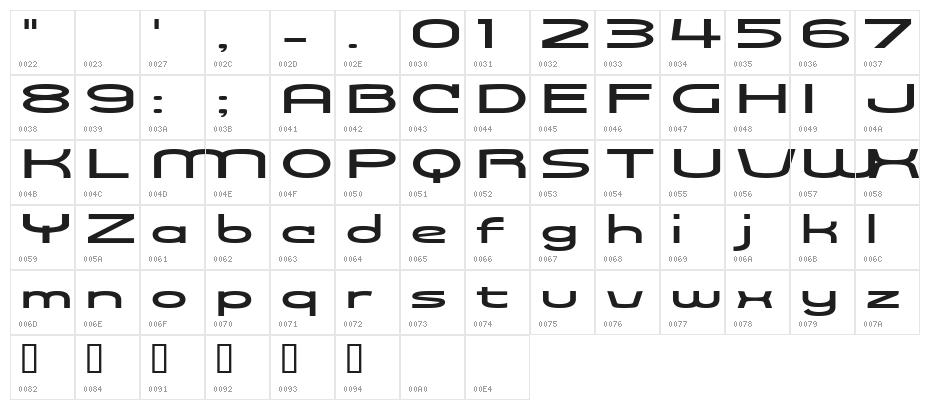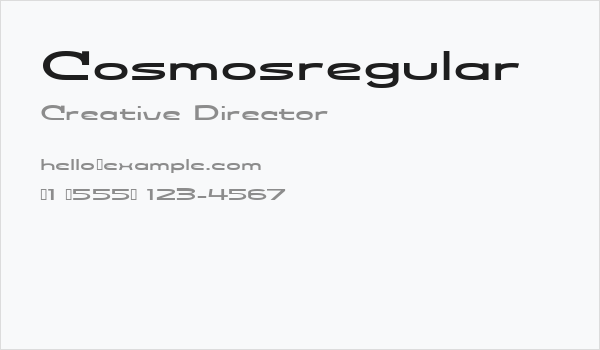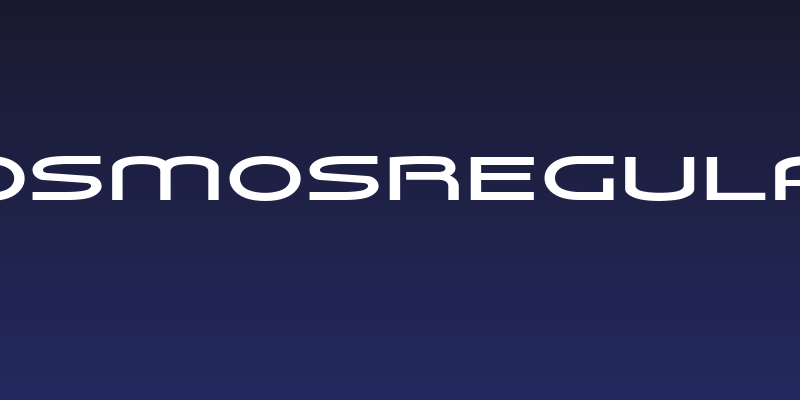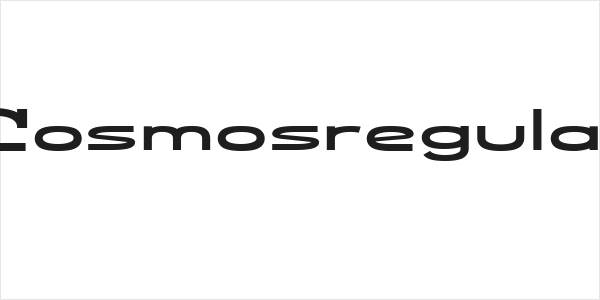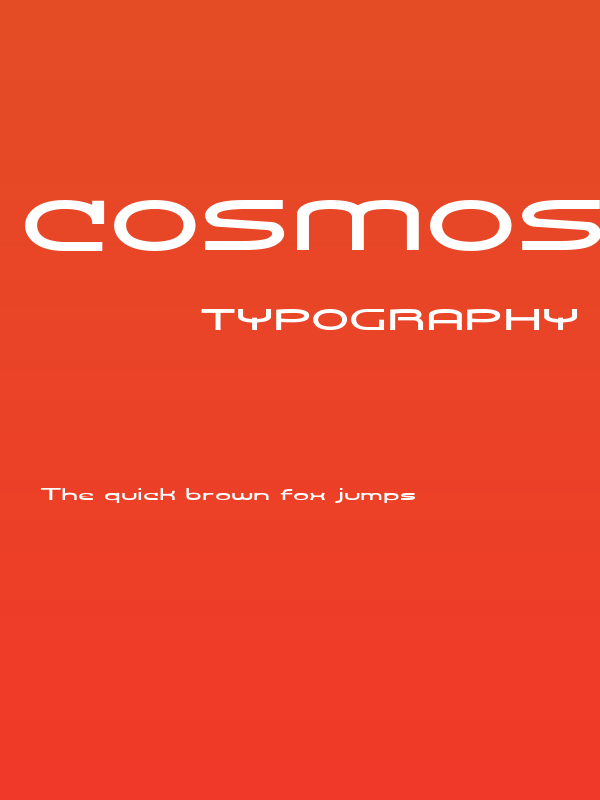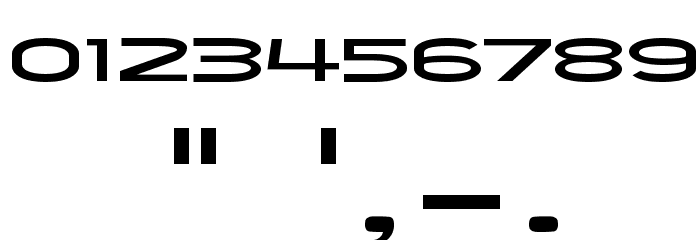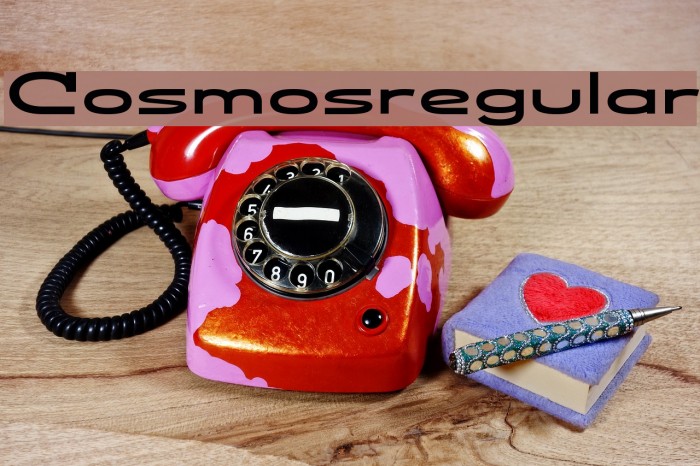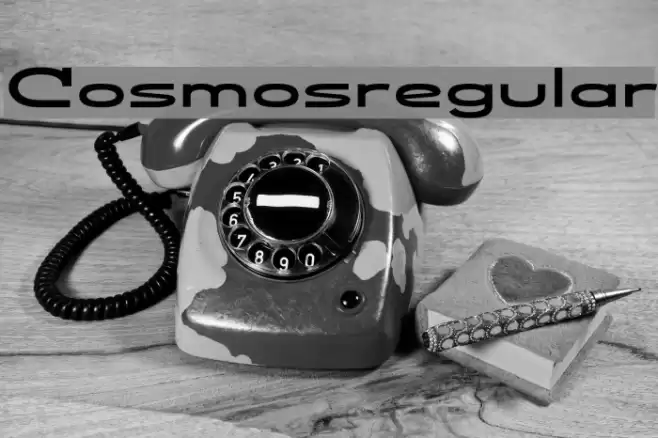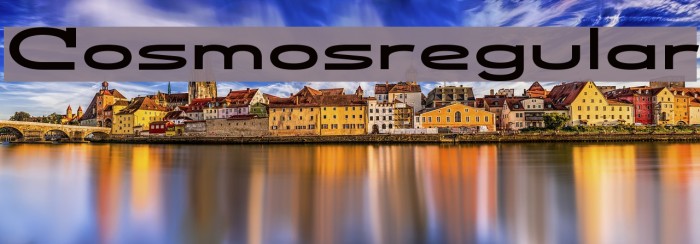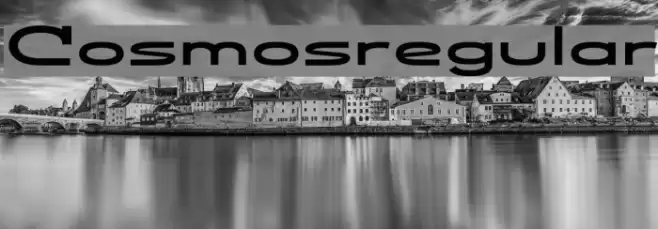
Cosmosregular Font
| Cas d'utilisation | Headlines, Logos, Digital interfaces |
| Projets proposés | Ideal for technology branding, sci-fi themed projects, modern web design, and innovative product packaging. |